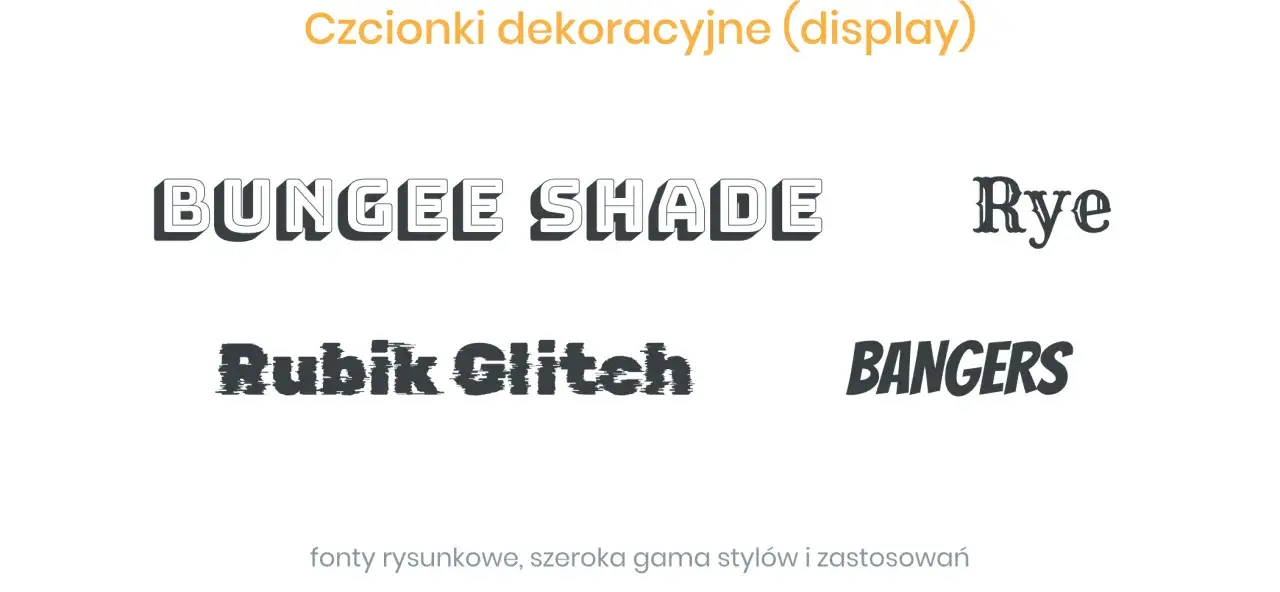
Najważniejsze rzeczy, które warto zapamiętać o współczesnej typografii
- Najlepszy efekt daje krój, który łączy czytelność, charakter i spójność z marką.
- W projektach cyfrowych coraz częściej wygrywają rodziny zmienne, bo pozwalają precyzyjnie dopasować grubość, szerokość i skalę bez mnożenia plików.
- W praktyce zwykle wystarczą 2 rodziny pisma i kilka dobrze dobranych odmian, zamiast całej kolekcji fontów.
- Dla tekstów użytkowych najbezpieczniej sprawdzają się kroje o wyraźnych kształtach liter, dobrych odstępach i pełnym wsparciu polskich znaków.
- To, co wygląda świeżo na mockupie, może nie działać w druku, w aplikacji albo na małym ekranie, dlatego test na realnym formacie jest obowiązkowy.
Co dziś naprawdę oznacza nowoczesny krój pisma
Ja patrzę na krój nie jak na ozdobę, ale jak na narzędzie komunikacji. Współczesny font ma być przede wszystkim czytelny, elastyczny i spójny z tonem marki, a dopiero potem efektowny. Jeśli litery mają dobrą proporcję, otwarte światła, sensowny kontrast i rytm, który nie męczy oka, projekt od razu wygląda dojrzalej.
- Wyraźna bryła liter - rozpoznawalne kształty pomagają czytać szybciej, zwłaszcza w interfejsach i na telefonach.
- Otwarte światła - przestrzeń wewnątrz znaków sprawia, że krój nie zlepia się optycznie przy mniejszych rozmiarach.
- Stabilny rytm - powtarzalne proporcje budują porządek i ułatwiają skład tekstu w wielu formatach.
- Elastyczność - rodziny zmienne potrafią zastąpić kilka osobnych plików, więc łatwiej je dopasować do ekranu, druku i responsywnych layoutów.
- Charakter bez przesady - dobry krój ma osobowość, ale nie walczy z treścią.
W praktyce „nowoczesność” nie oznacza tu fajerwerków. Chodzi raczej o to, żeby typografia była aktualna w sposobie działania: wspierała odbiór, dobrze składała się w systemie i nie psuła wrażenia po pierwszym kontakcie. Gdy te cechy są dopracowane, można sensownie porównywać konkretne rodzaje krojów.
Jakie rodzaje krojów najczęściej wyglądają współcześnie
Jeśli mam szybko ocenić kierunek, patrzę na rodzinę, z której pochodzi krój. Różne style dają zupełnie inny efekt: jedne budują neutralność i technologiczną precyzję, inne dają ciepło albo redakcyjny charakter. Poniżej zestawiam te, które w praktyce najczęściej pracują dobrze.
| Rodzaj kroju | Najlepsze zastosowanie | Co daje wizualnie | Na co uważać |
|---|---|---|---|
| Geometric sans | Marki technologiczne, minimalizm, landing page | Porządek, precyzję, nowoczesny chłód | Może wydać się zbyt sterylny, jeśli nie dodasz ciepła w kolorach lub układzie |
| Neo-grotesk | Interfejsy, systemy projektowe, komunikacja korporacyjna | Neutralność i uniwersalność | Bez dobrego spacingu robi się przeciętny i mało wyrazisty |
| Humanist sans | Serwisy contentowe, edukacja, usługi | Więcej miękkości i „ludzkiego” charakteru | Przy zbyt ciężkiej wersji traci lekkość |
| Editorial serif | Magazine look, premium branding, kultura, moda | Elegancję i wyraźniejszą hierarchię | W małych rozmiarach wymaga dobrego testu czytelności |
| Display / experimental | Hero sekcje, plakaty, kampanie, krótkie hasła | Odrębność i zapamiętywalność | Nie nadaje się do długich bloków tekstu |
Najczęściej zaczynam od humanistycznego sansa albo neo-grotesku, bo dają bezpieczną bazę. Gdy potrzebuję więcej klasy albo napięcia wizualnego, dokładam szeryf w nagłówkach lub w materiałach redakcyjnych. Dopiero potem sięgam po bardziej odważne rozwiązania, bo to one najłatwiej przechodzą z „modne” w „przekombinowane”.
Jak dobrać font do marki i kanału, żeby nie zgadywać
Ja zwykle zaczynam nie od samej nazwy kroju, tylko od miejsca, w którym ma pracować. Inny font sprawdzi się w aplikacji z danymi, inny w e-booku, a jeszcze inny w reklamie premium, która ma przyciągnąć uwagę w dwie sekundy. Ten kontekst jest ważniejszy niż sama moda.- Określ rolę kroju - osobno dla nagłówków, tekstu głównego i akcentów.
- Sprawdź język - pełny zestaw polskich znaków, interpunkcję i kerning, czyli ręczną korektę odstępów między parami liter.
- Dopasuj skalę - dla tekstu użytkowego najczęściej dobrze działają 16-18 px, interlinia 1.45-1.65 i wiersz długości około 55-75 znaków.
- Ogranicz liczbę odmian - 3-4 grubości zwykle wystarczą, a 2 rodziny pisma to w większości projektów bezpieczny pułap.
- Testuj na realnym materiale - z prawdziwym copy, zdjęciami i formatami docelowymi, nie tylko na pięknym podglądzie.
W badaniu Monotype 76% projektantów wskazało czytelność i dostępność jako priorytet. Dla mnie to praktyczna wskazówka: jeśli mam wybierać między charakterem a funkcją, najpierw bronię funkcji, bo to ona decyduje, czy typografia faktycznie pracuje dla marki. Gdy baza jest ustawiona, łatwiej wychwycić błędy, które najczęściej psują efekt.
Najczęstsze błędy, które odbierają projektowi świeżość
Najwięcej problemów nie wynika z samego kroju, tylko z tego, jak go użyto. Widziałem już bardzo dobre fonty, które wyglądały słabo tylko dlatego, że ktoś przeciął je złym kontrastem, za dużym rozstrzeleniem albo kompletnie nieprzemyślaną hierarchią.
- Test hierarchii - sprawdzam, czy nagłówek, lead i tekst główny naprawdę różnią się od siebie bez chaosu.
Jeśli któryś z tych punktów odpada, szukam dalej. W typografii dużo łatwiej poprawić wybór na etapie testów niż ratować całą identyfikację po wdrożeniu, a dobrze dobrany krój zwykle pracuje latami bez potrzeby ciągłych poprawek.